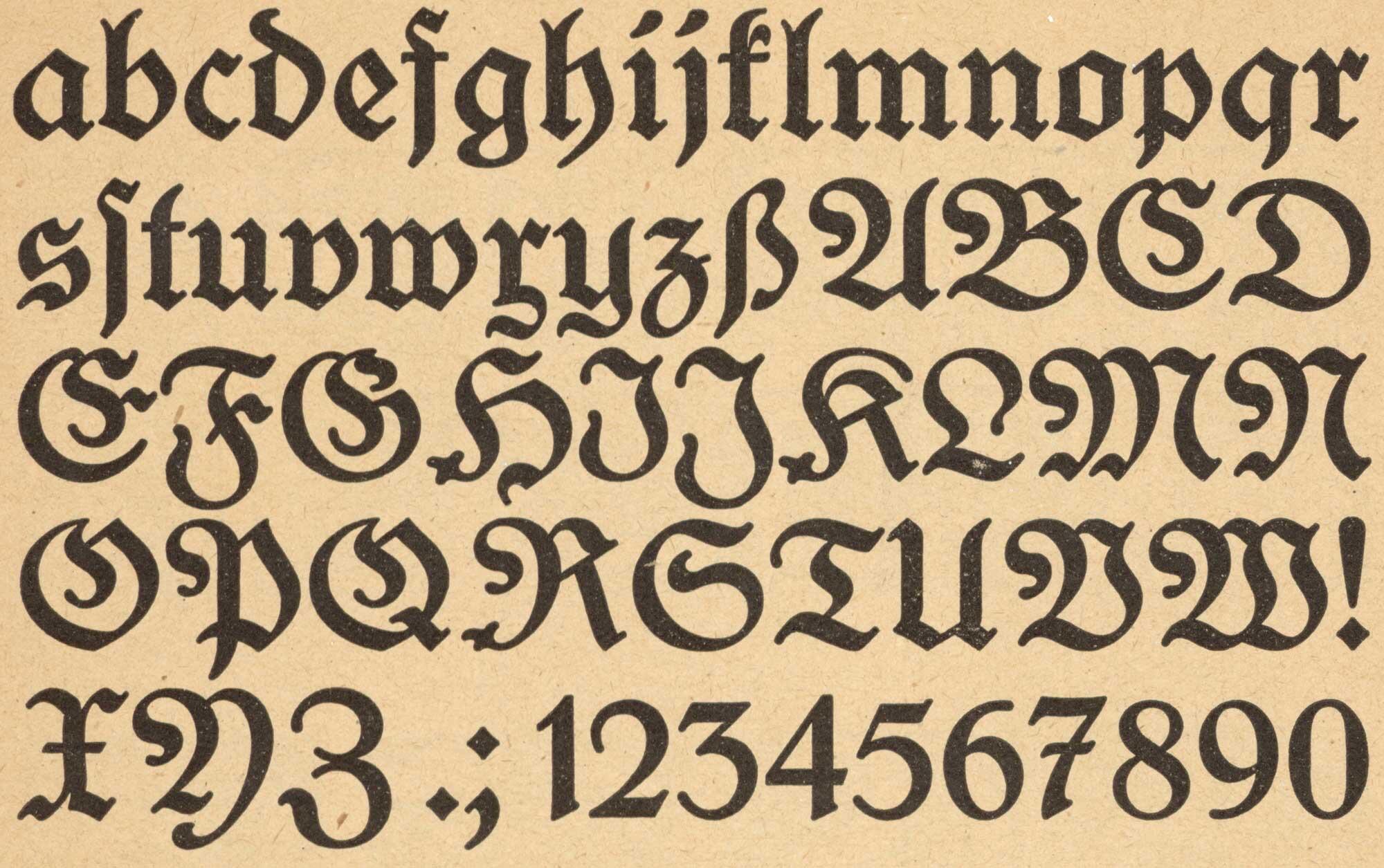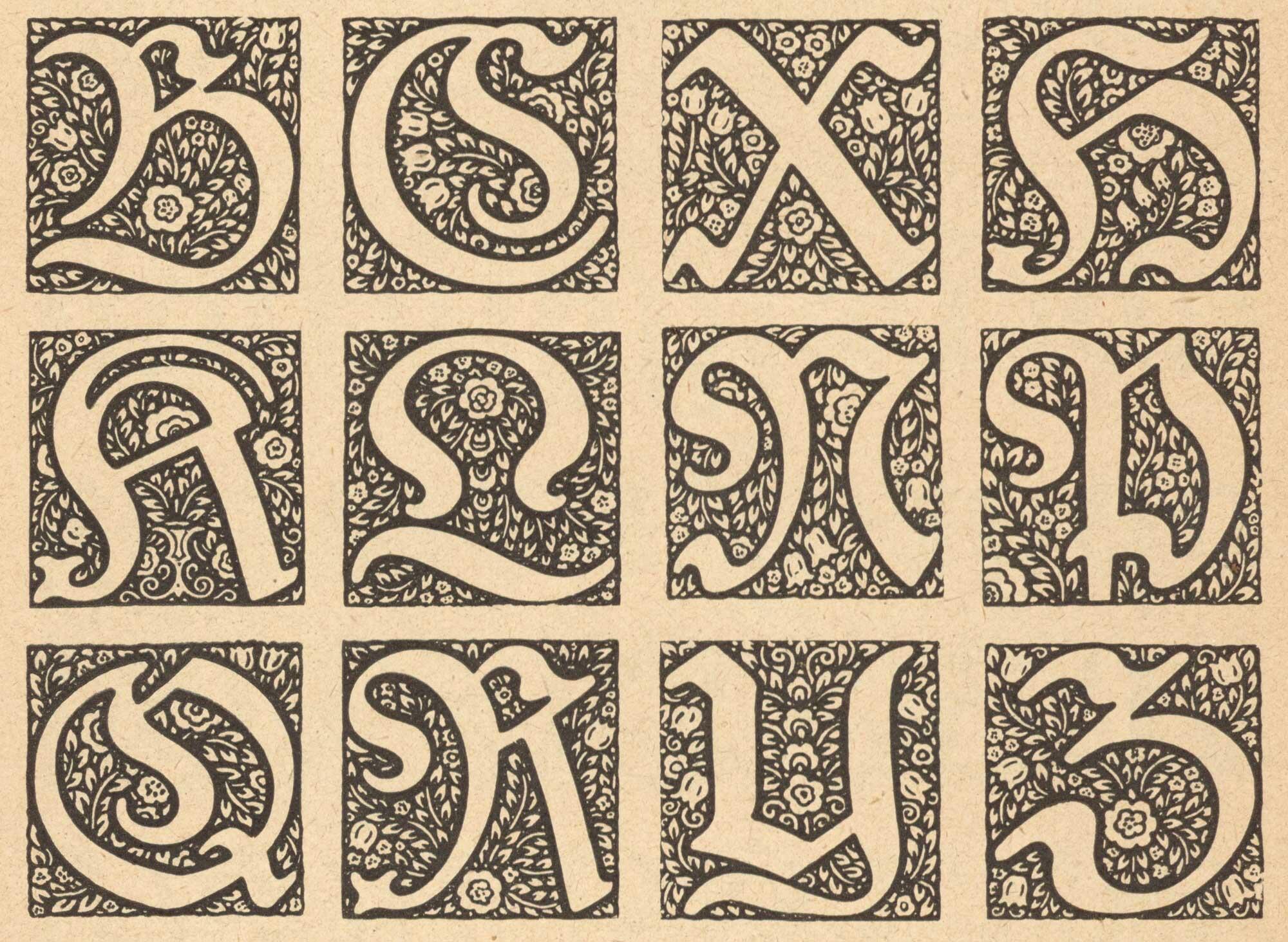
- 1915
- Gebrochene Schrift
Die Buhe-Fraktur von Walter Buhe erschien 1915 bei der D. Stempel AG und wurde bis in die 1930er-Jahre weiter ausgebaut: mager, halbfett, fett, schmalfett und Initialen.
Eine Digitalisierung einzelner Schnitte gibt es von Gerhard Helzel.